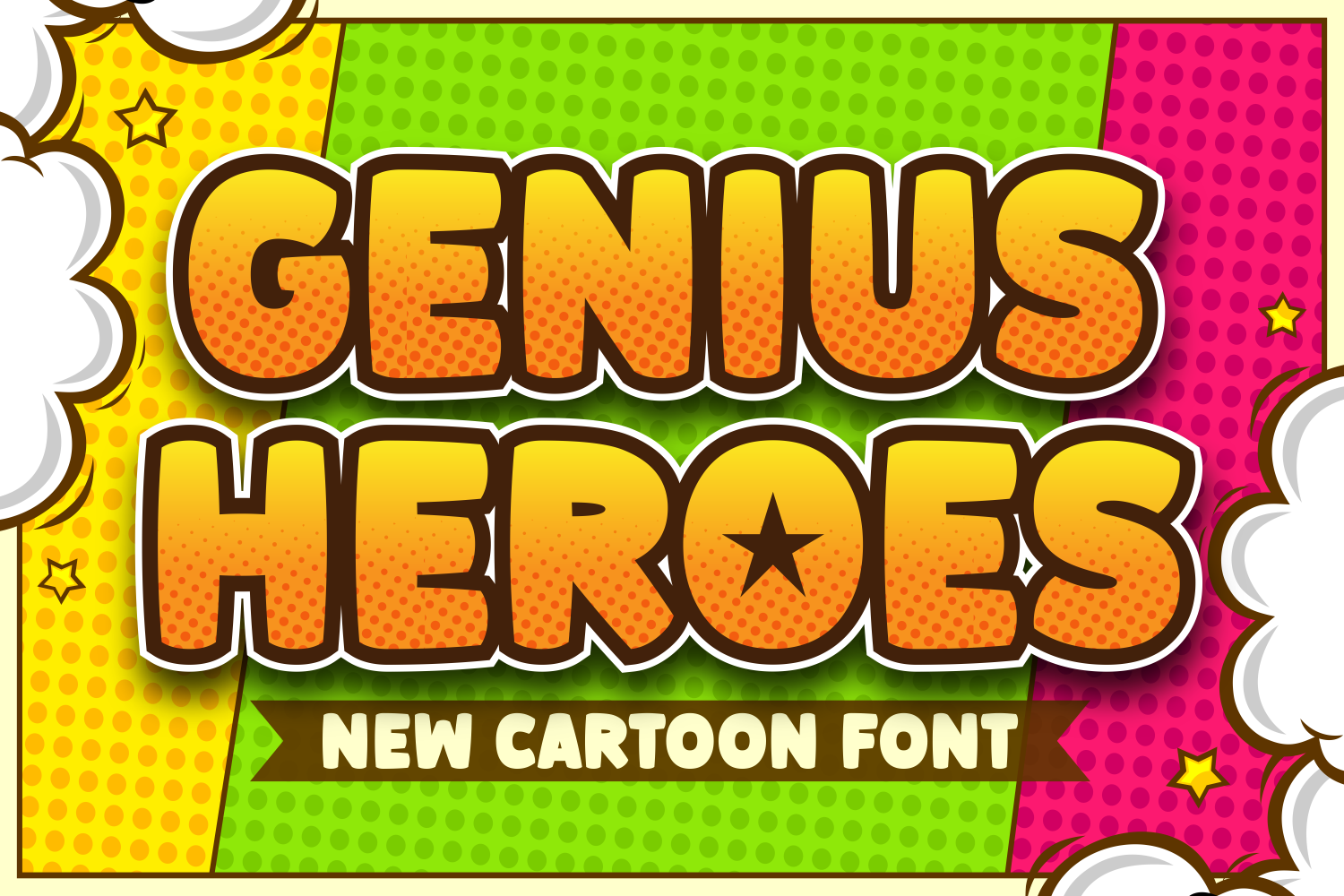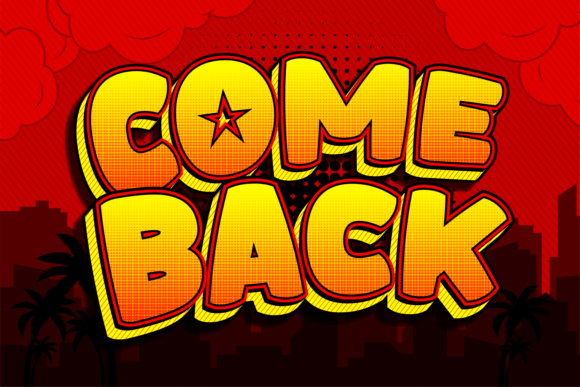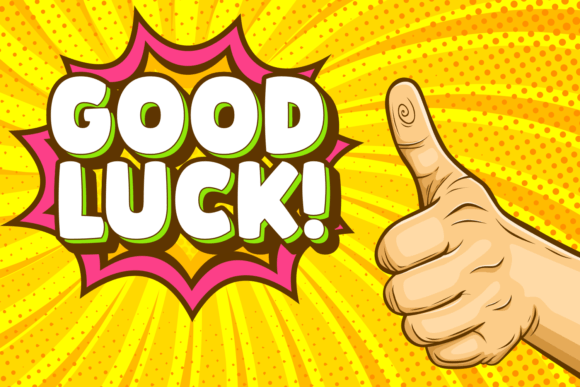
فونت Genius Heroes انگلیسی
دانلود فونت Genius Heroes انگلیسی Font جنیوس هیروز |
| ⭐ مجموعه فونت | دانلود فونت انگلیسی قهرمانان نابغه Font Genius Heroes |
| ⭐ توضیحات | Genius Heroes یک فونت نمایشگر ضخیم و چاق است. این تایپ فیس الهام گرفته از کارتونی همه چیزهایی را که برای ایجاد تایپوگرافی چشمگیر نیاز دارید، دارد. آن را به کتابخانه فونت های خود اضافه کنید و از آن برای همه پروژه هایی که نیاز به زیبایی شناسی جسورانه دارند استفاده کنید!